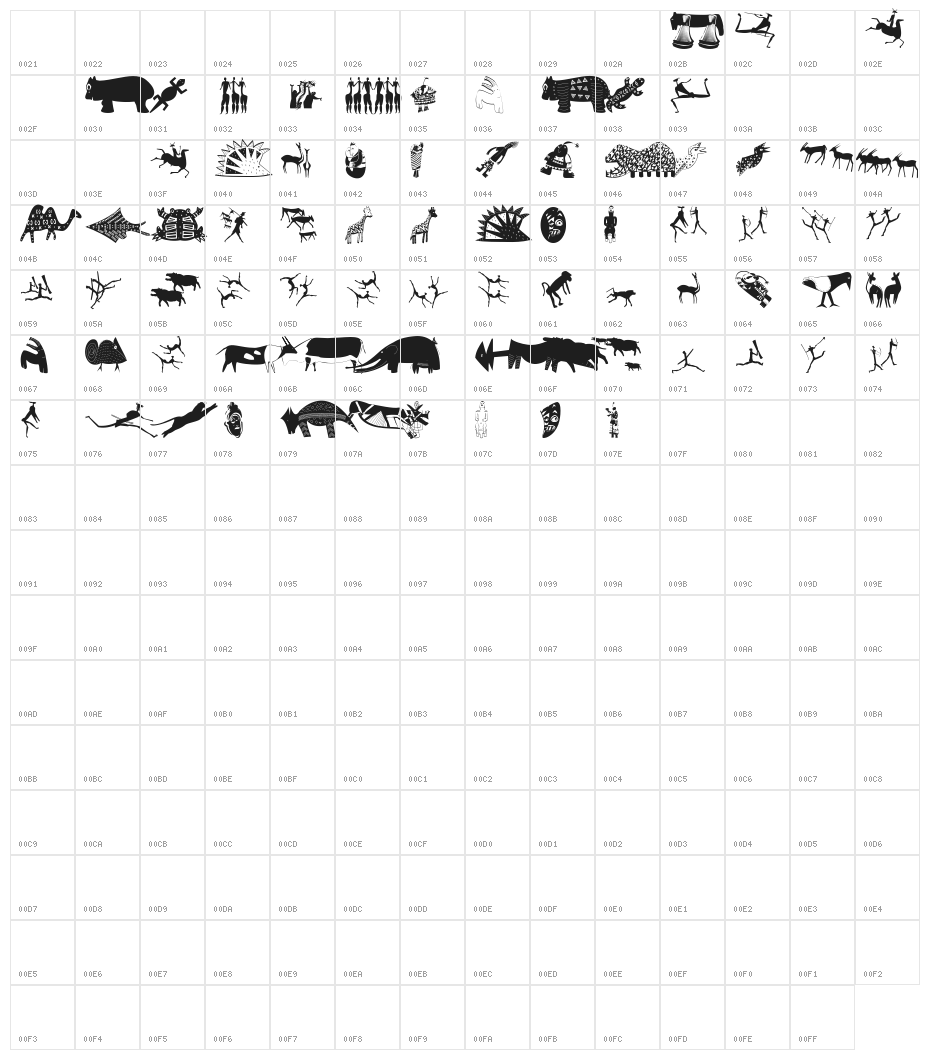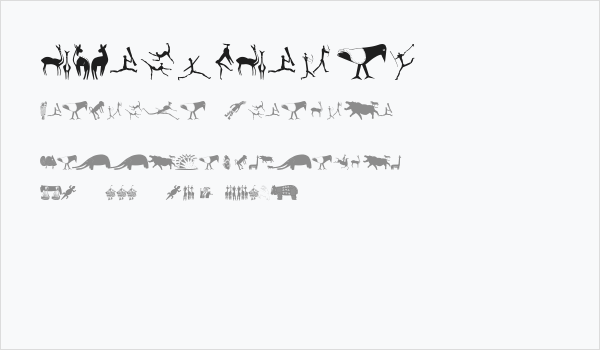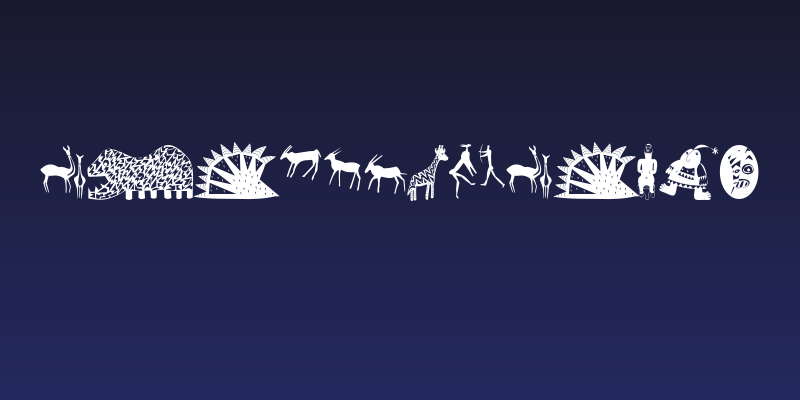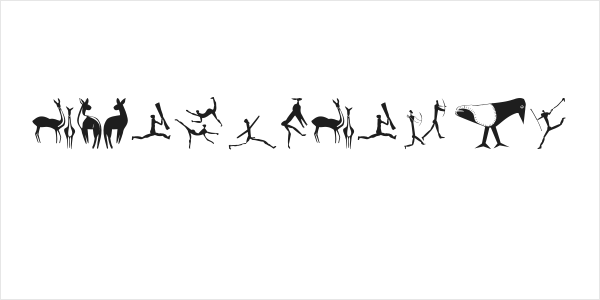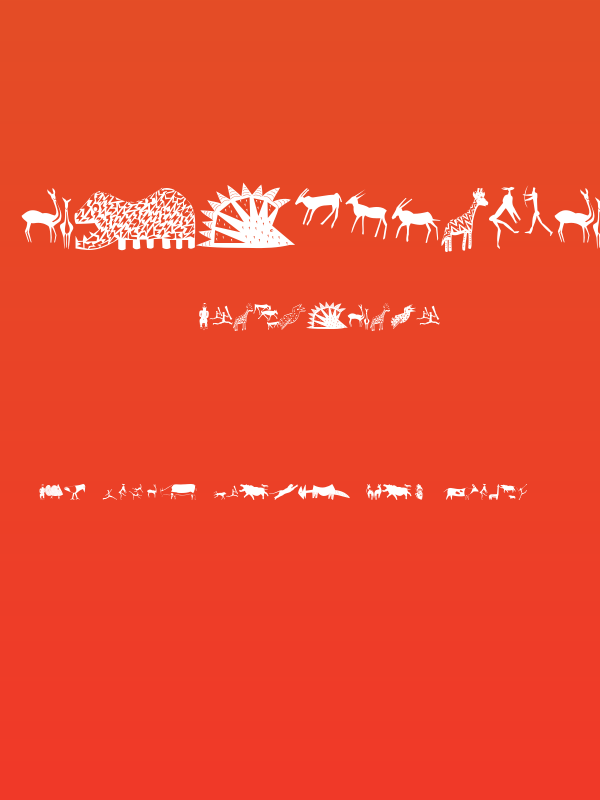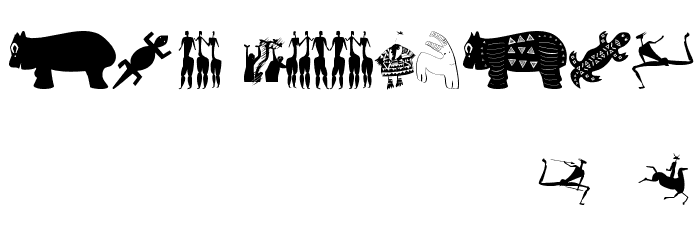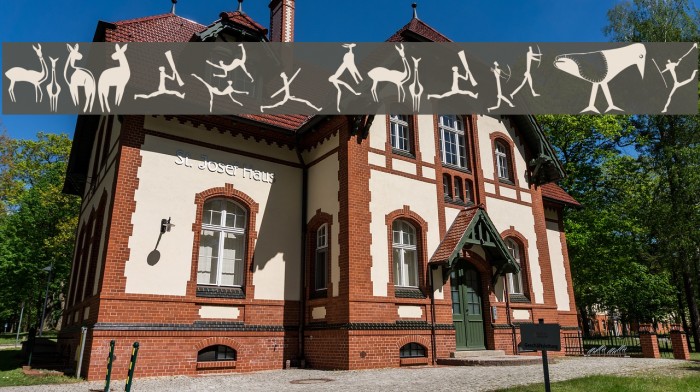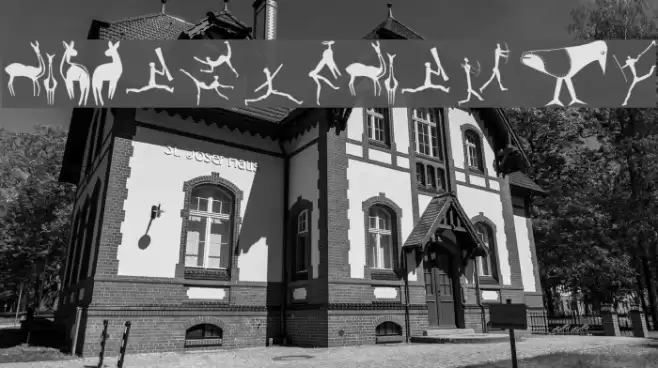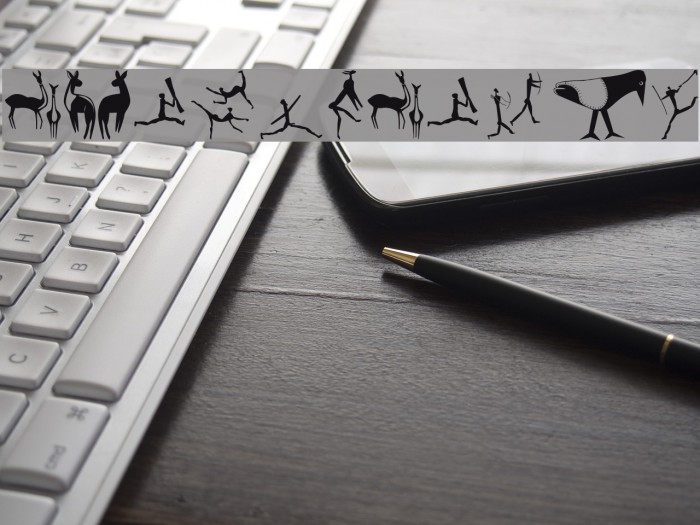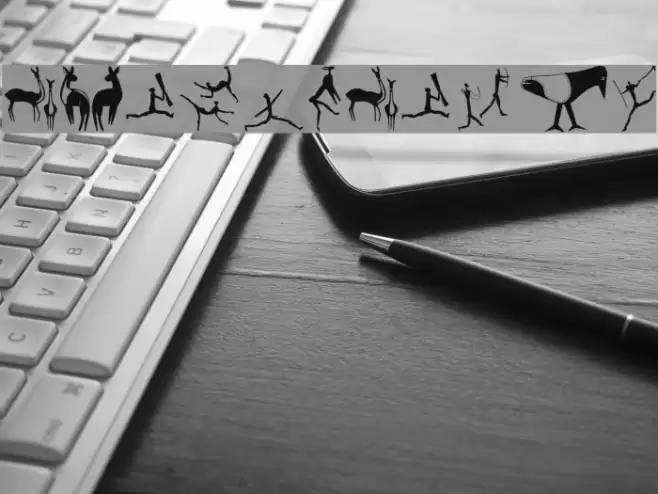
AfriquArtes Font
| Caso d'uso | Logos, Art projects, Cultural events |
| Progetti proposti | Ideal for cultural projects, educational materials, art exhibitions, and themed events that require a touch of African heritage and artistic flair. |